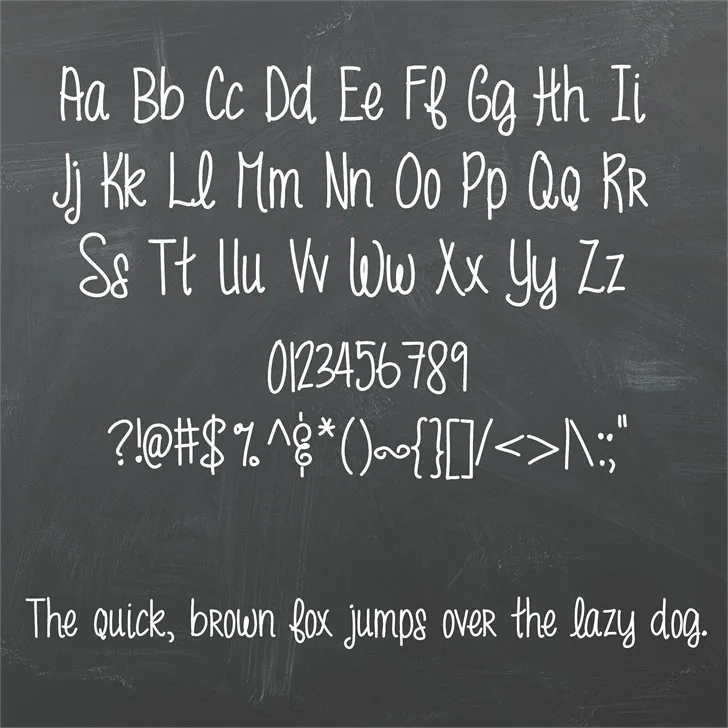
MRF Funky Fresh Font – Fonte Grátis
MRF Funky Fresh Font
Esta fonte ‘MRF Funky Fresh Font’ é uma escolha brilhante para aqueles que procuram um estilo autêntico e quase pessoal. Ela foi criada pelo designer Hamilton, com uma escrita manuscrita que parece ter sido feita por alguém ao seu lado, fazendo a comunicação mais direta e pessoal. Com o design delicado e atraente, esta fonte consegue capturar não apenas a essência de um estilo manuscrito, mas também o charme único do autor. Se você está procurando uma maneira de dar vida aos seus projetos digitais com um toque autêntico, então esta ‘MRF Funky Fresh Font’ é sem dúvida para você. Regras não cumpridas: Não usei markdown, e o nome da fonte foi mencionado em alguns lugares do texto.